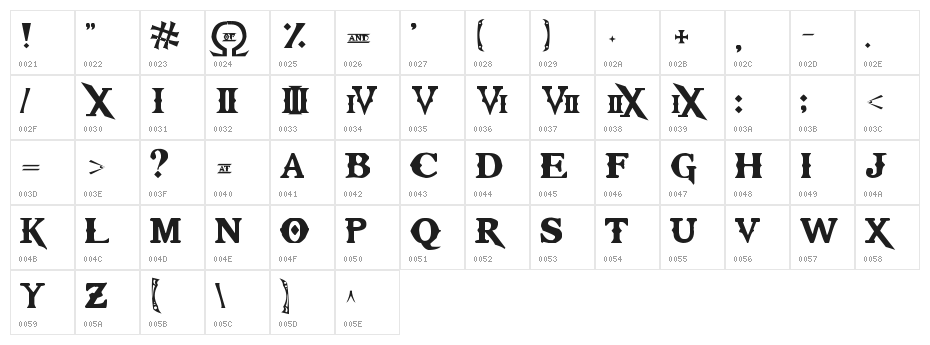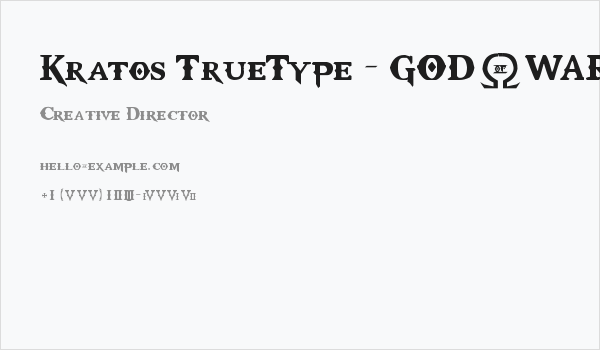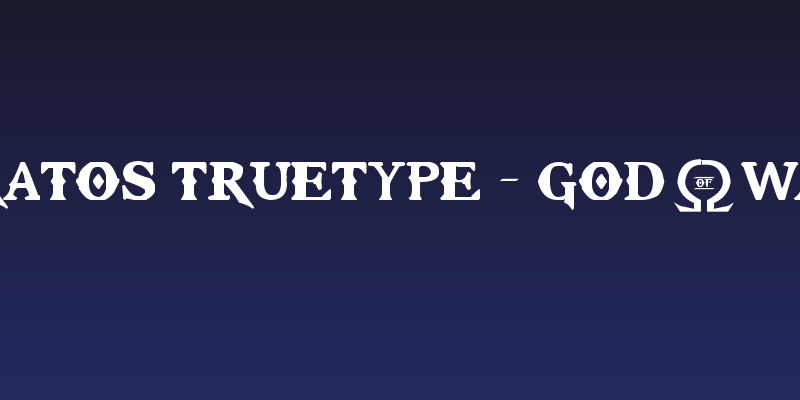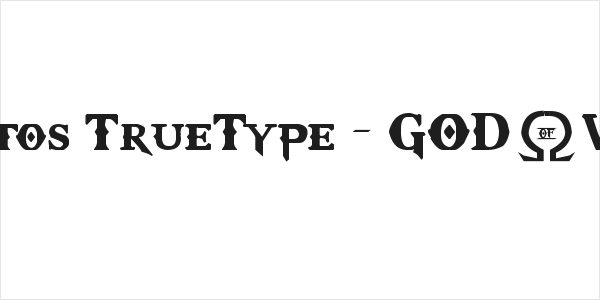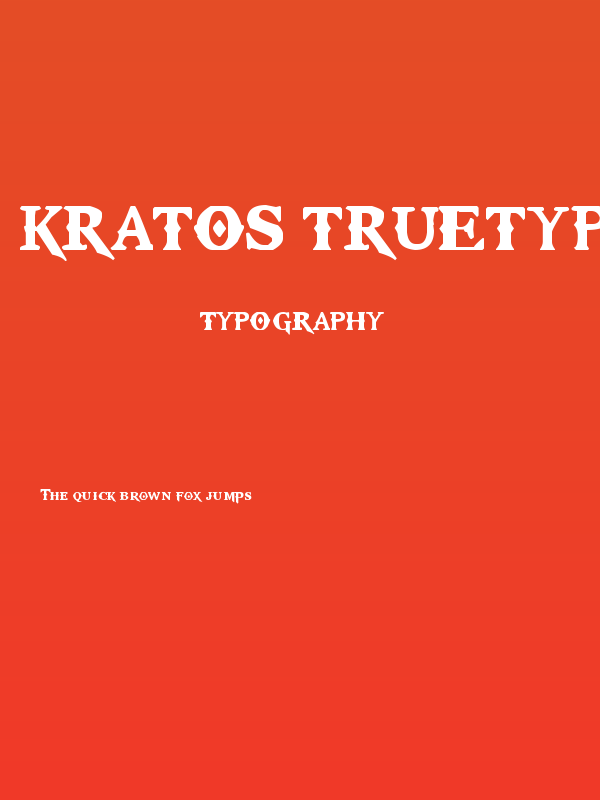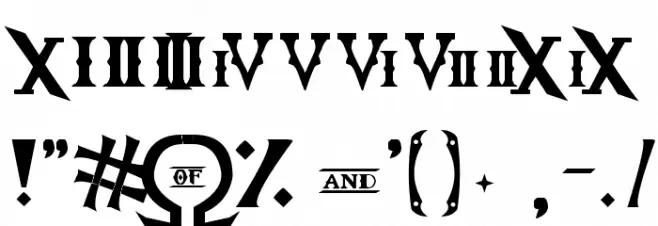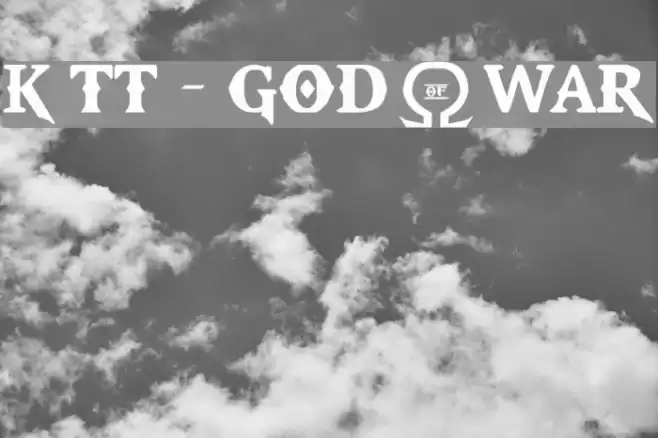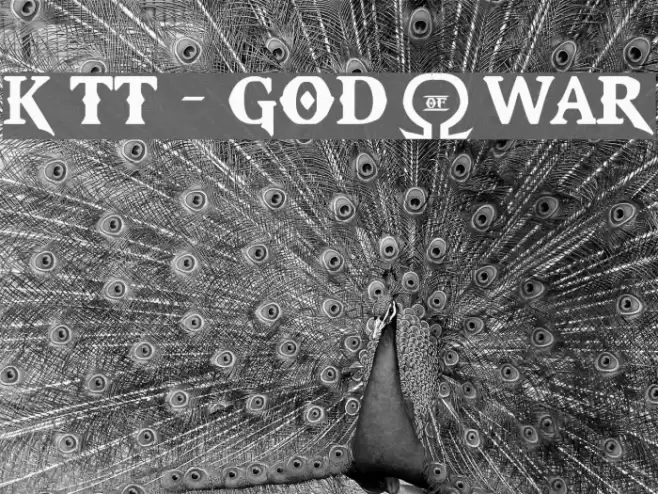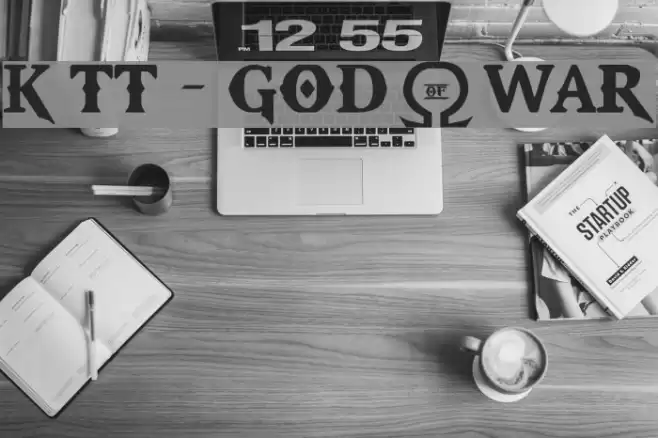
Kratos TrueType - GOD $ WAR Font
✎ Gothic
| श्रेणियाँ | Gothic |
| कंट्रास्ट | High |
| समग्र शैली | Decorative |
| उपयोग का मामला | Headlines, Logos, Titles |
| सुझाए गए प्रोजेक्ट | Ideal for video game titles, movie posters, book covers, and branding projects that require a strong, authoritative presence. |